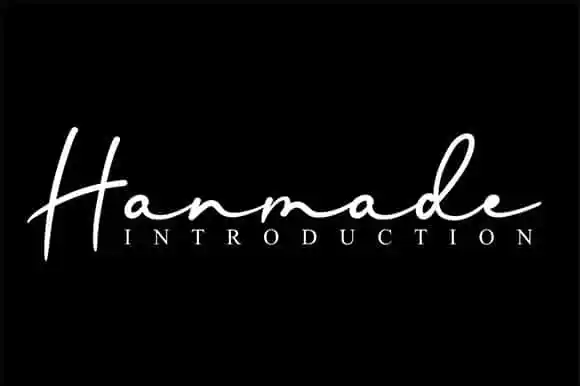
Hanmade Handwritten Font – Download Grátis
Descubra a frescura da Hanmade Handwritten Font com uma descrição que captura seu encanto para diversos projetos criativos. Este script-font é perfeito para adicionar um toque personalizado e delicado, ideal para aplicar em diversas mídias digitais como wall displays, postagens nas redes sociais e até mesmo como design de logotipos. Seu charme natural e sua elegância vão agradecer qualquer projeto que demande uma escrita à mão real. Este font é perfeito para wedding invitations ou cartões-postais, revestir embalagens de produtos com um toque criativo, incorporar em design fotográfico ou até mesmo adicionar um ar delicado e único como watermark nas suas criações digitais. Seja ele o coração de seu projeto gráfico ou a mão que dá vida à sua ideia, Hanmade é a font perfeita para qualquer necessidade de projetos que exigem uma escrita à mão. Além disso, este font também é uma ótima escolha para estilizar materiais impressos. As letras curvas e as bordas suaves são perfeitamente adaptadas às etiquetas de produtos ou ao design dos cartões-postais, oferecendo um acabamento único e imprimível que pode adicionar valor a qualquer produto ou material. Seja em estilos mais tradicionais ou naquelas criaturas modernas, Hanmade é uma font ideal para quem procura expressar algo verdadeiramente pessoal no mundo digital.